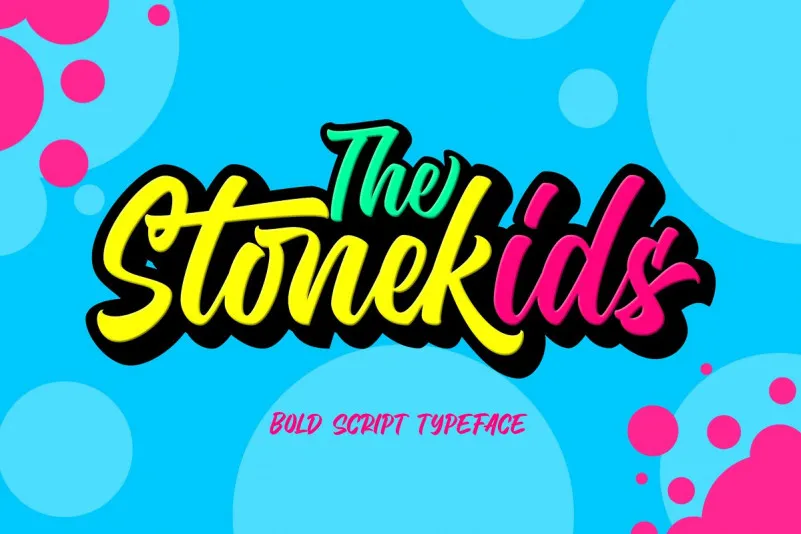
Esta fonte Stonekids Bold Script é uma criação moderna e sofisticada de 24Design, inspirada nas letras de mão escritas, logotipos de script bold e fontes infantis. Com suas linhas elegantes e detalhes cuidadosamente criados em cada letra, ela oferece um resultado visual único e atraente para qualquer projeto. Stonekids está disponível com recursos de tipo aberto e suporte multilíngue para acento, tornando-a perfeita não apenas para logotipos, cartazes e mochilas, mas também para capas de livros, camisetas e embalagens. Como uma fonte script bold, ela oferece uma sensação vibrante e moderna que complementará sua identidade visual de forma inovadora. Seja você um designer gráfico ou qualquer pessoa que desfruta de criar conteúdo visual, Stonekids é o ideal para levar seu design ao próximo nível.